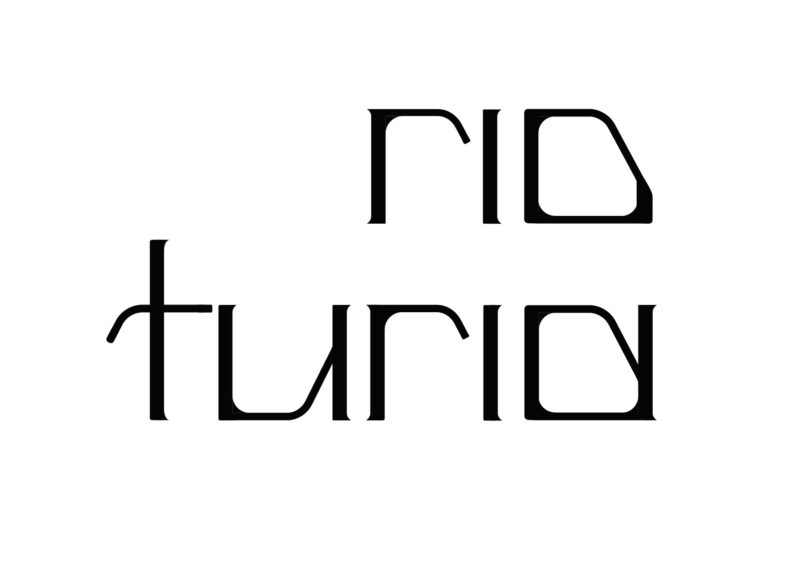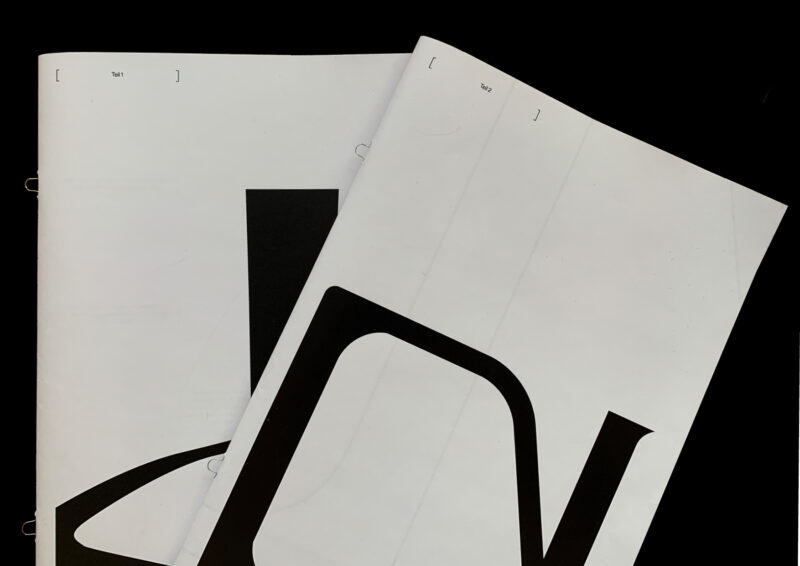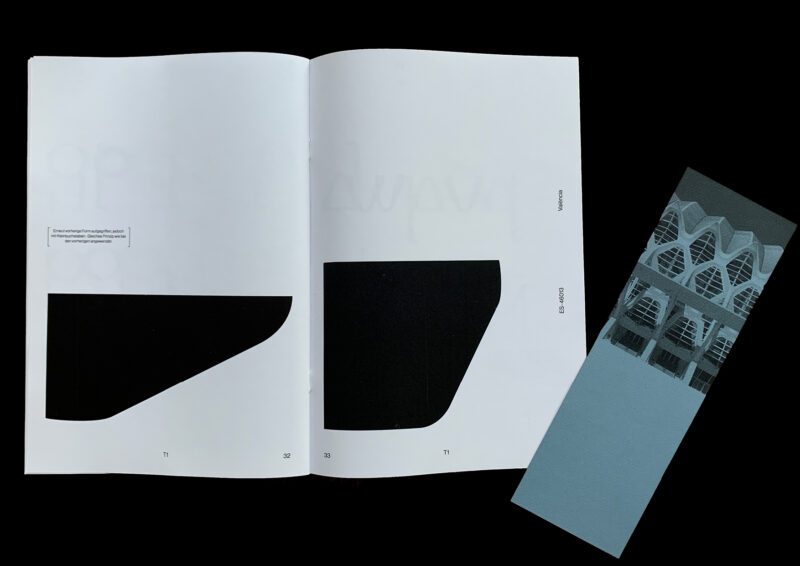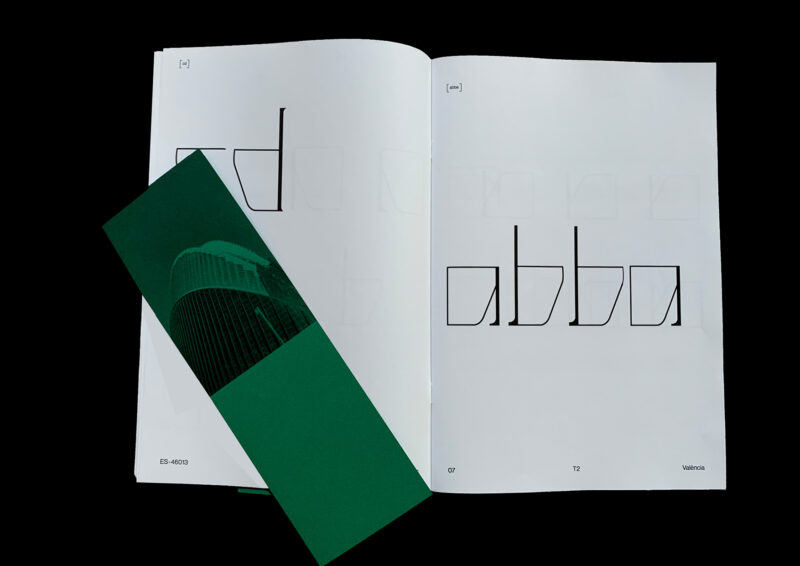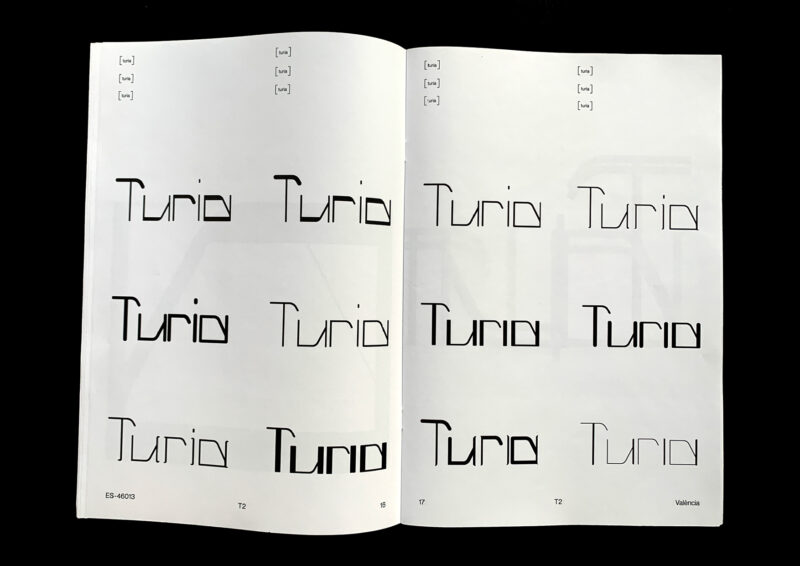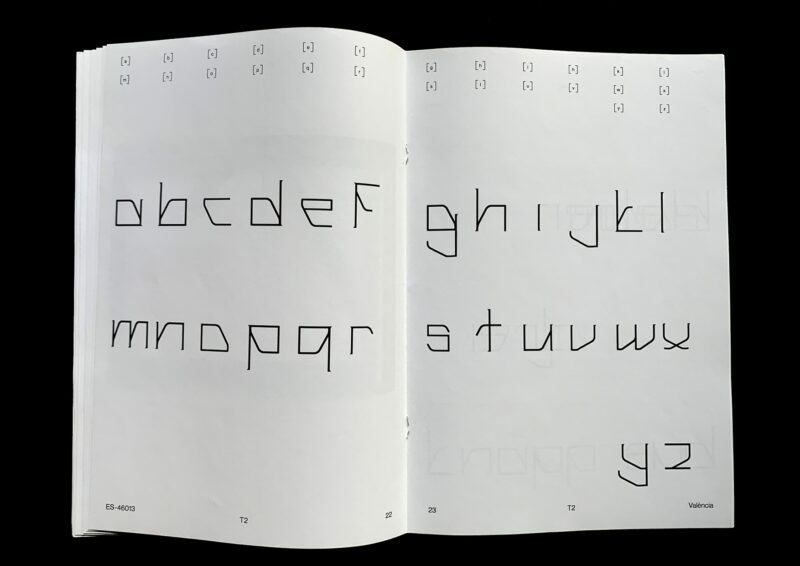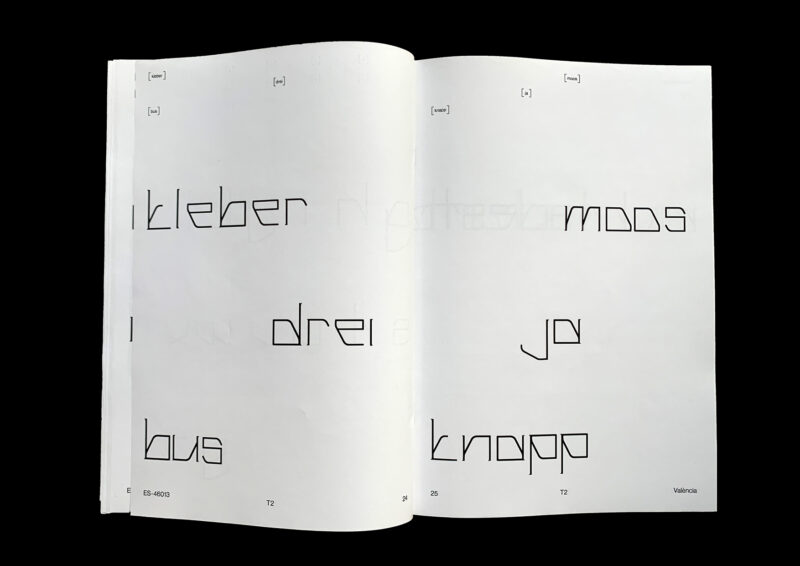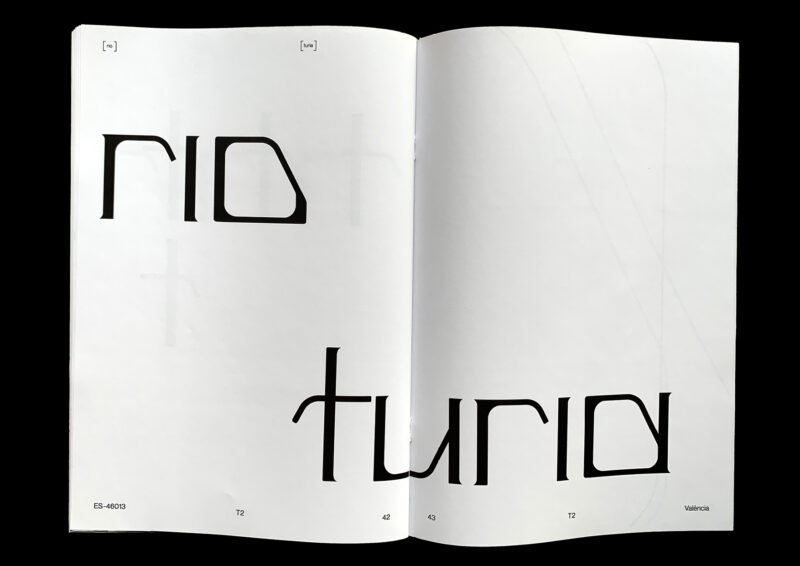
Turia
Ausgehend von dem experimentellen Gebäude- und Parkkomplexes «Ciutat de les Arts i les Ciències» in Valencia ist der Schriftentwurf «Turia» entstanden. Die architektonische Formensprache des Areals ist in den Schriftcharakter überführt und prägt dessen Visualität. Deutlich spürbar ist im finalen Schriftentwurf der Bezug zu Geometrie, Proportion und Rhythmus der Gebäudefenster. Beim Entwerfen der lateinischen Schriftzeichen werden die formale Referenzen hinterfragt und neu ausgelotet.